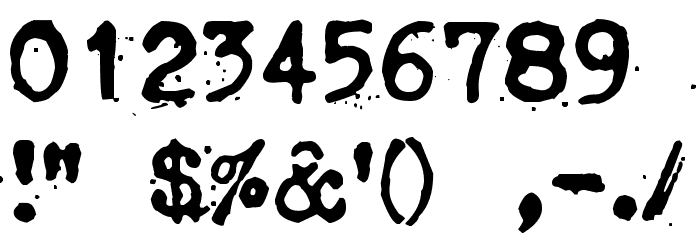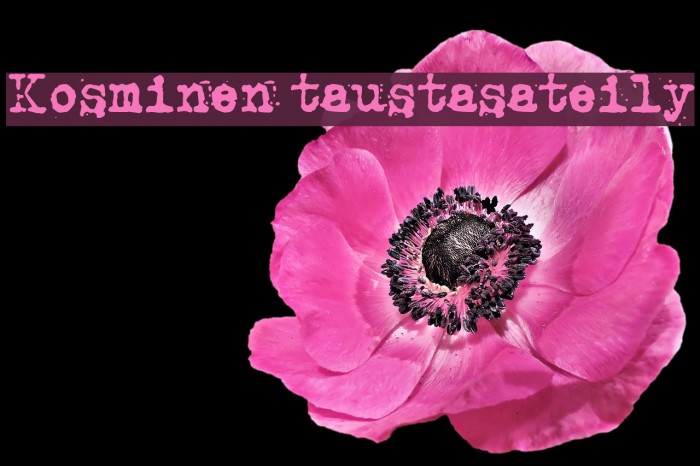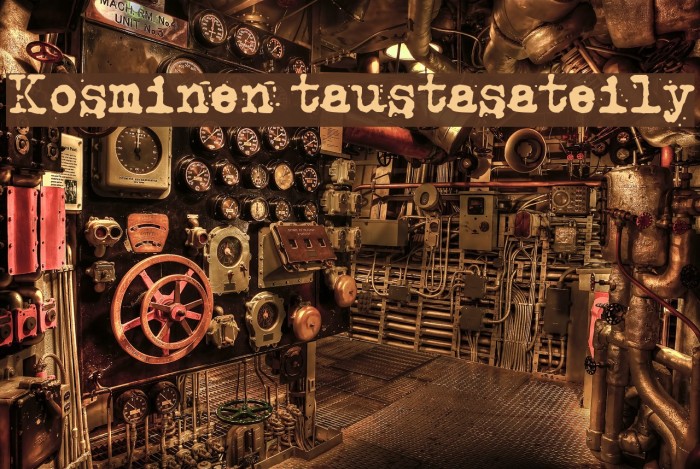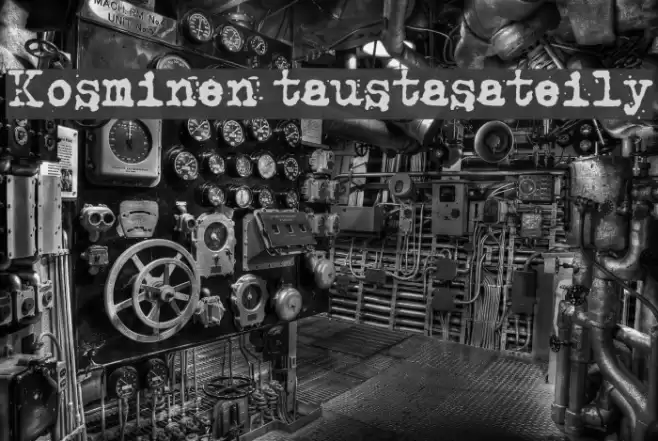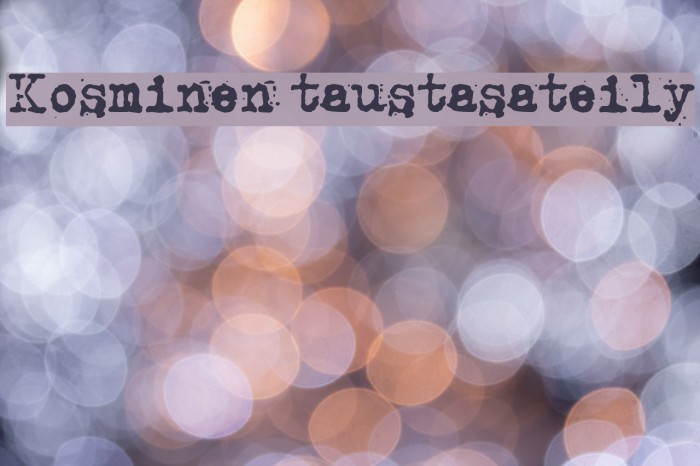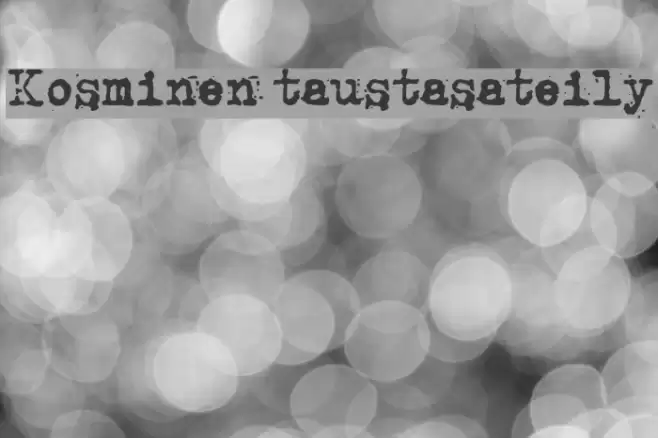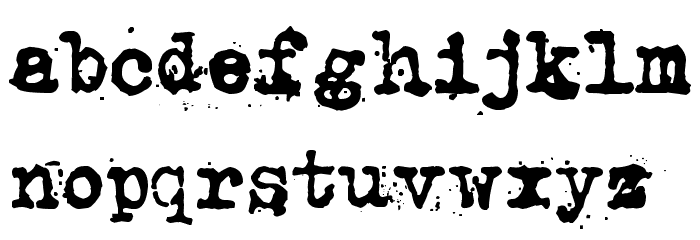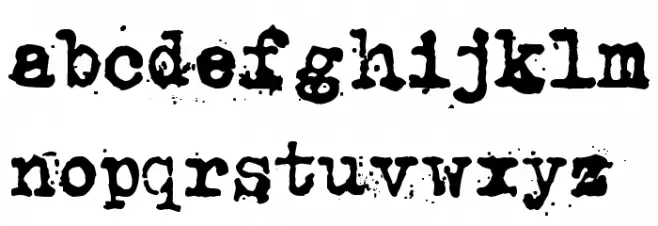
Kosminen taustasateily Font
✎ Typewriter
| カテゴリ | Typewriter |
| 全体的なスタイル | Vintage, Grunge |
| 用途 | Headlines, Posters, Branding |
| おすすめプロジェクト | Ideal for posters, album covers, branding for edgy or alternative products, and any design needing a bold, vintage touch. |